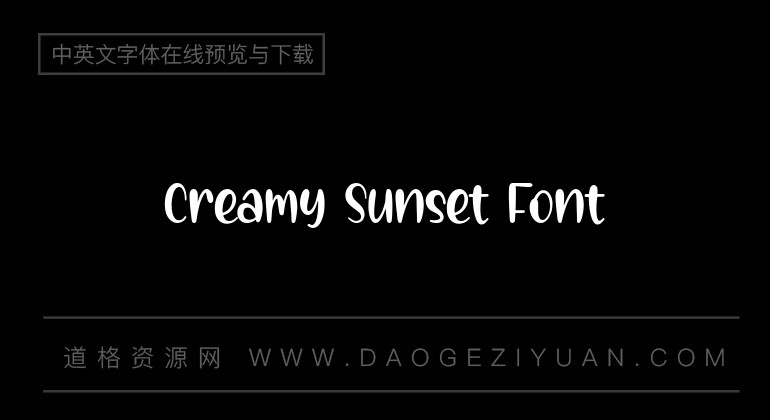
Creamy Sunset Font 是一种手写风格的字体,其设计风格充满了温暖、柔和和自然的感觉。该字体拥有流畅的线条和圆润的笔画,特别适合用于设计温馨、舒适、自然、有机的场景。Creamy Sunset Font 字体的大小和颜色均可自由调整,可以轻松地与其他设计元素相结合,打造出独特而具有吸引力的设计效果。内容介绍
Creamy Sunset Font是一款非常不错的手写艺术字体,具有很好的视觉感,适合于文化类的宣传设计、商业类品牌的广告和产品包装设计以及个性化文字排版等较多场景。